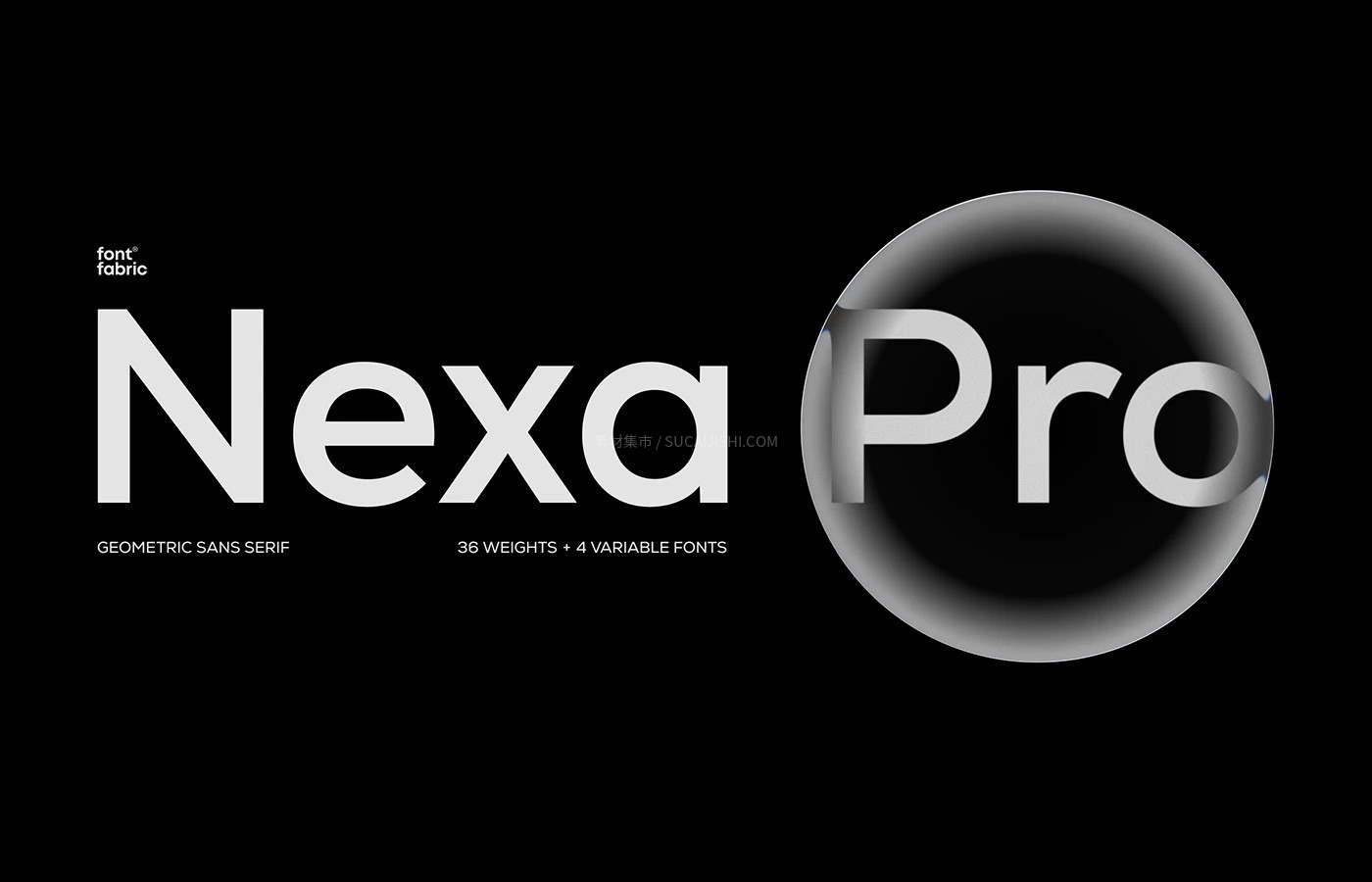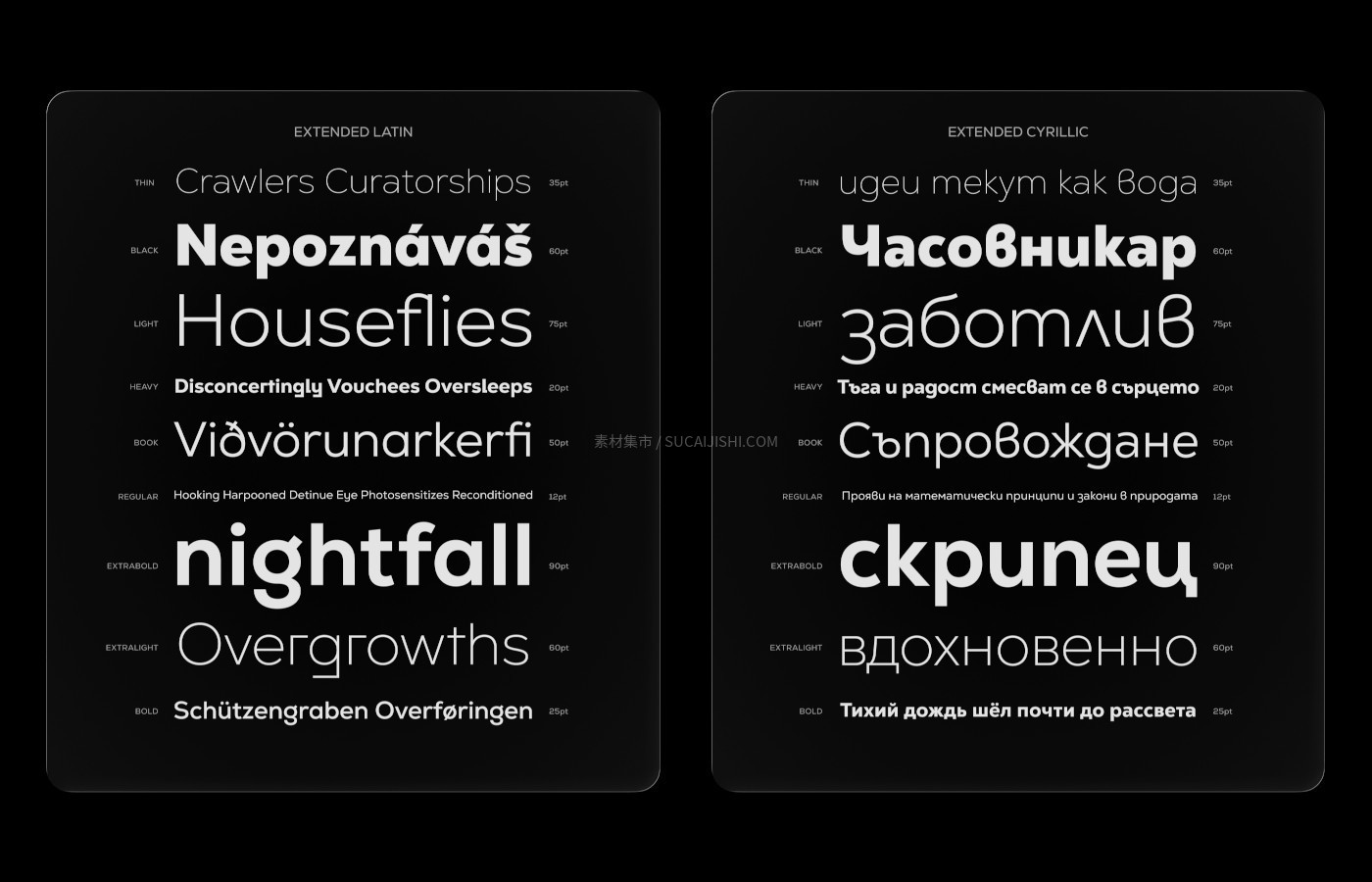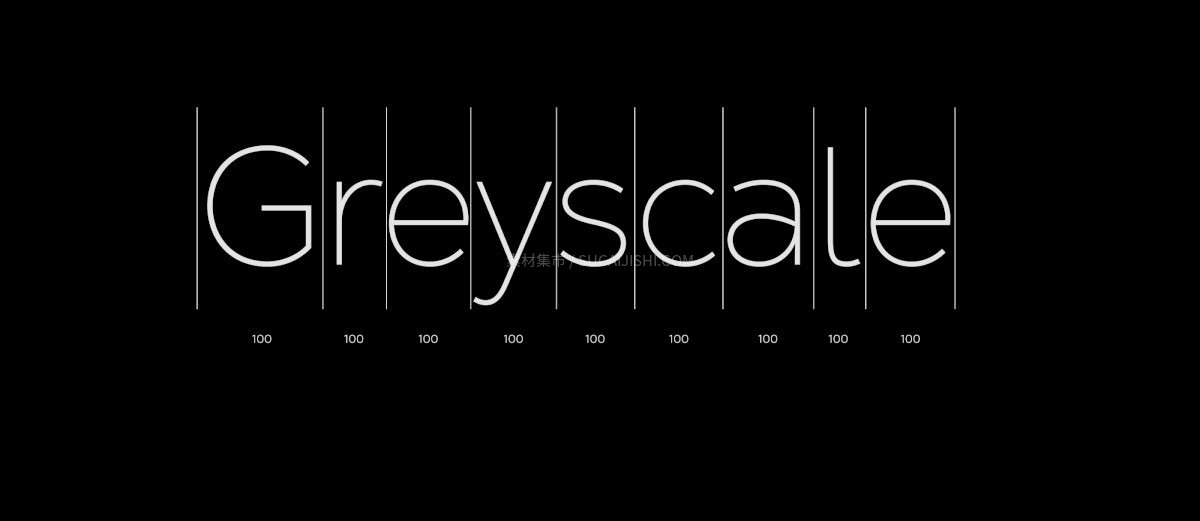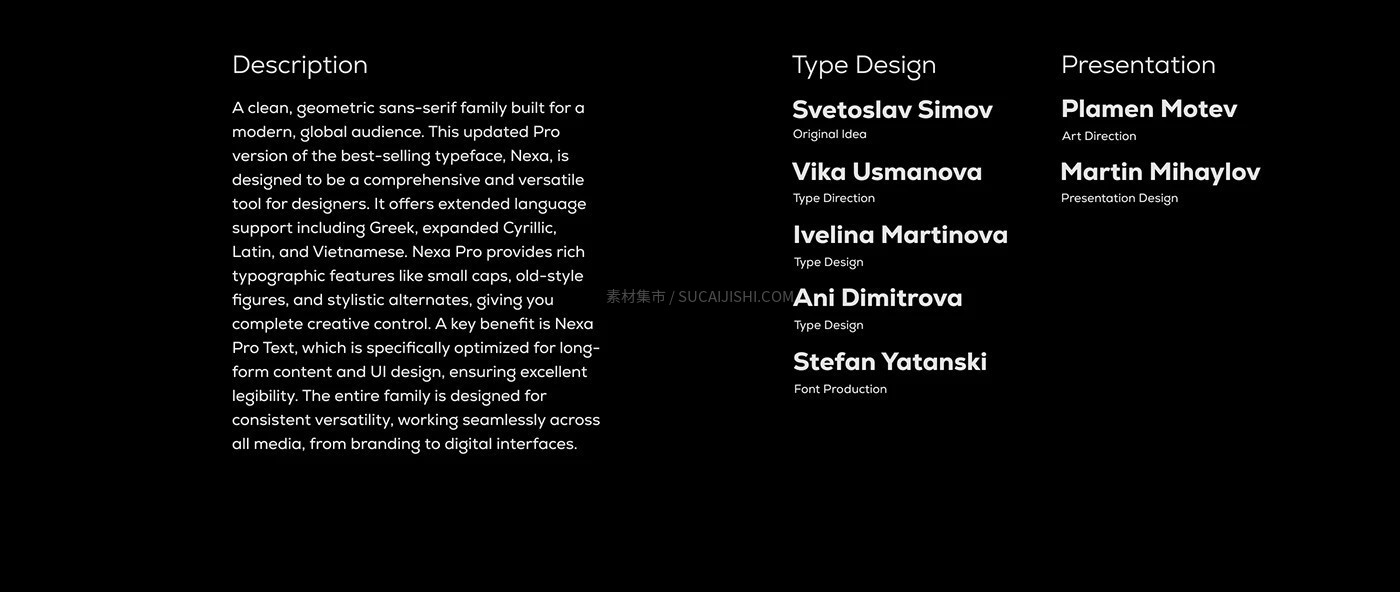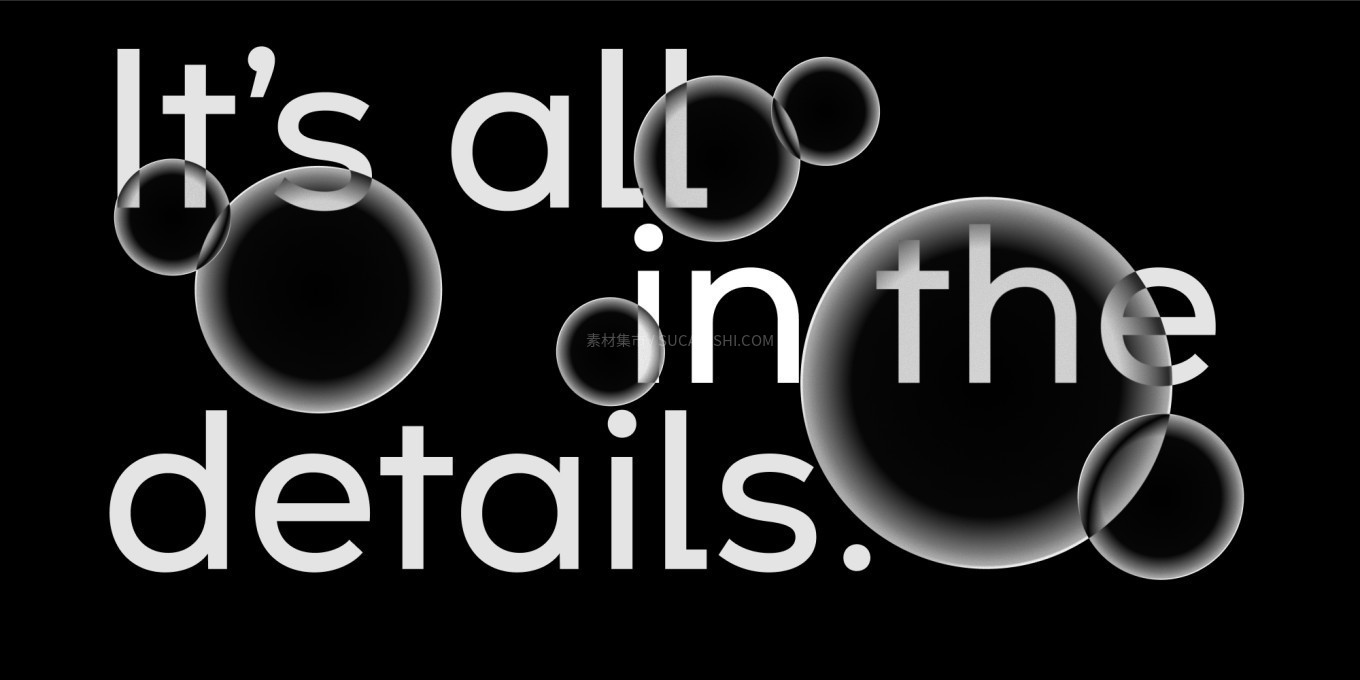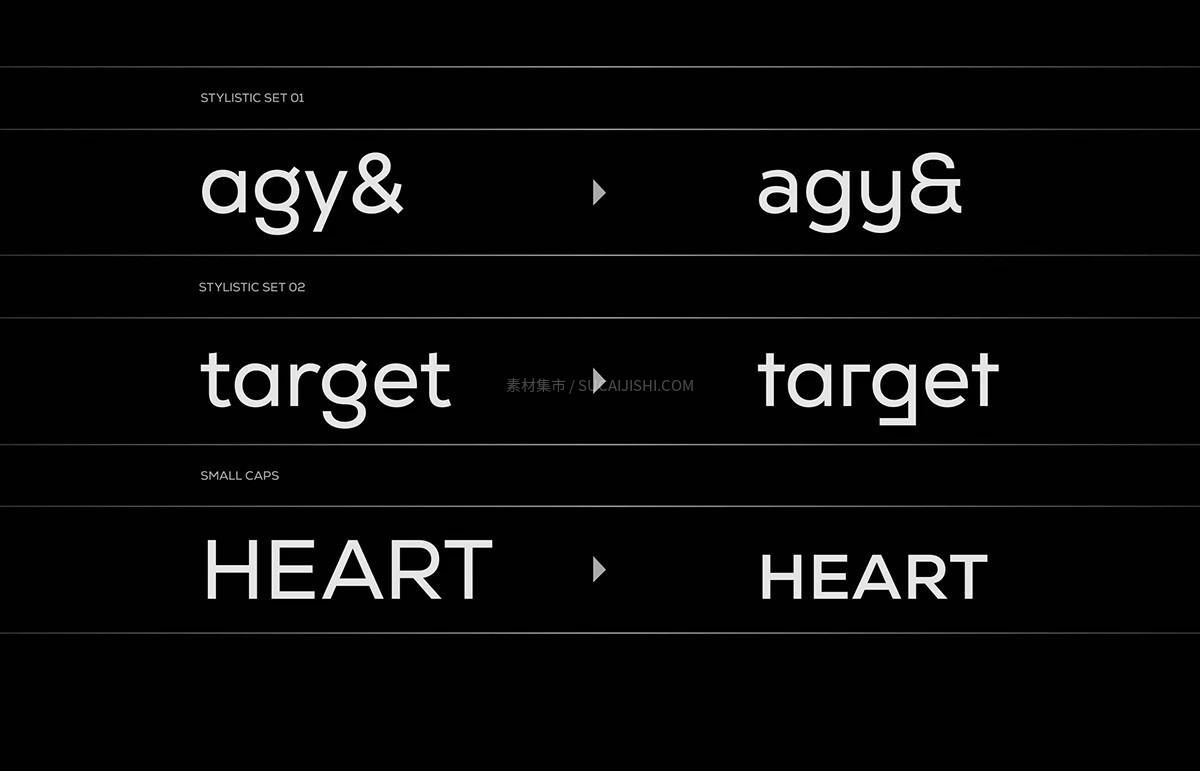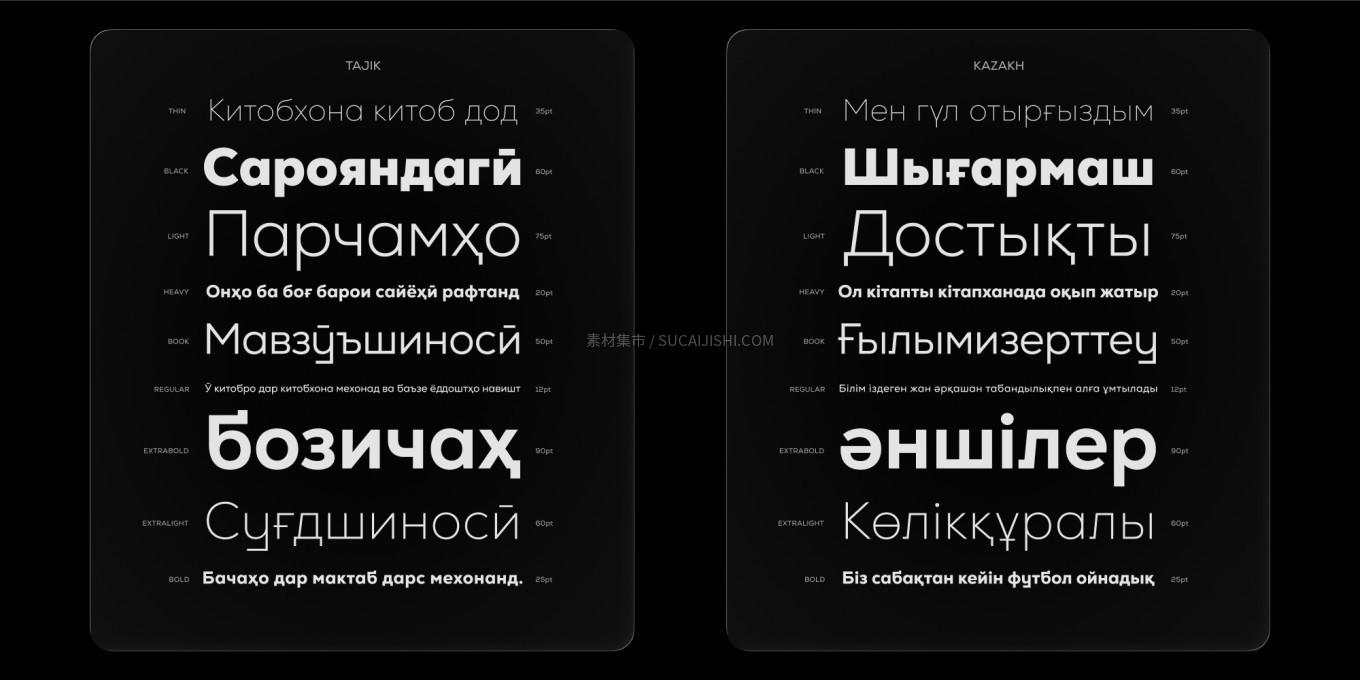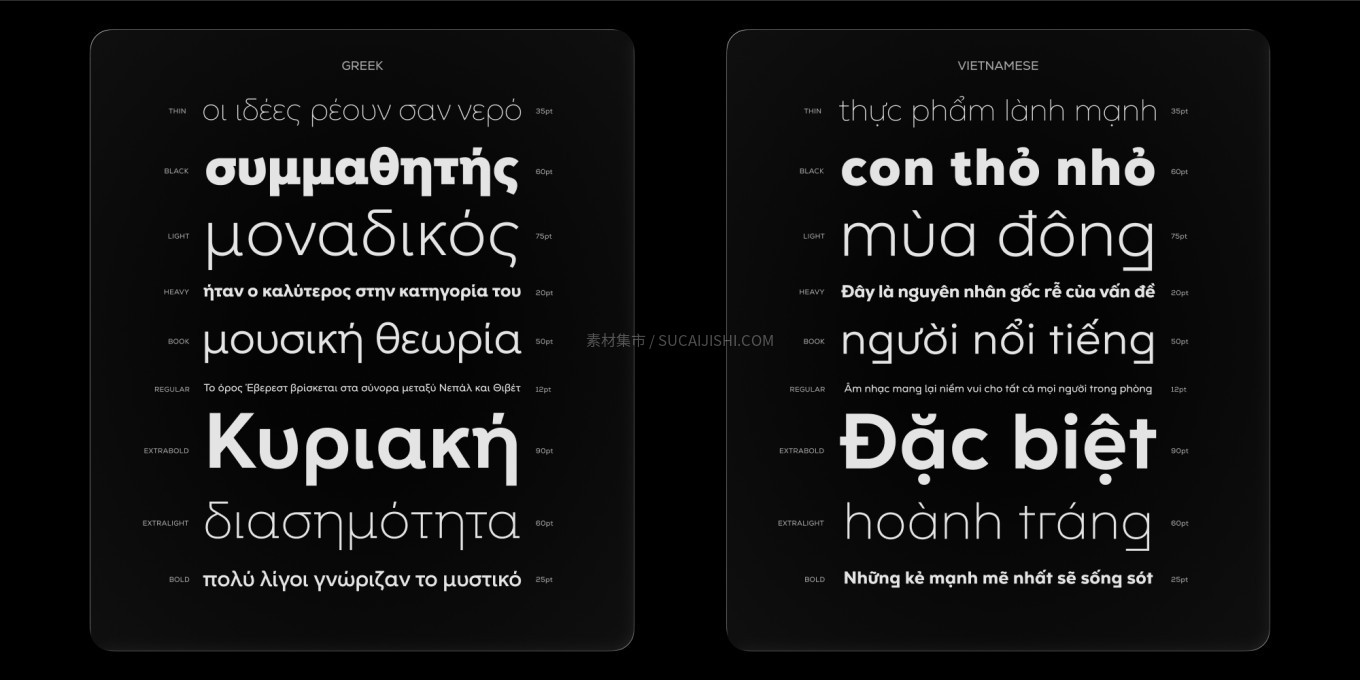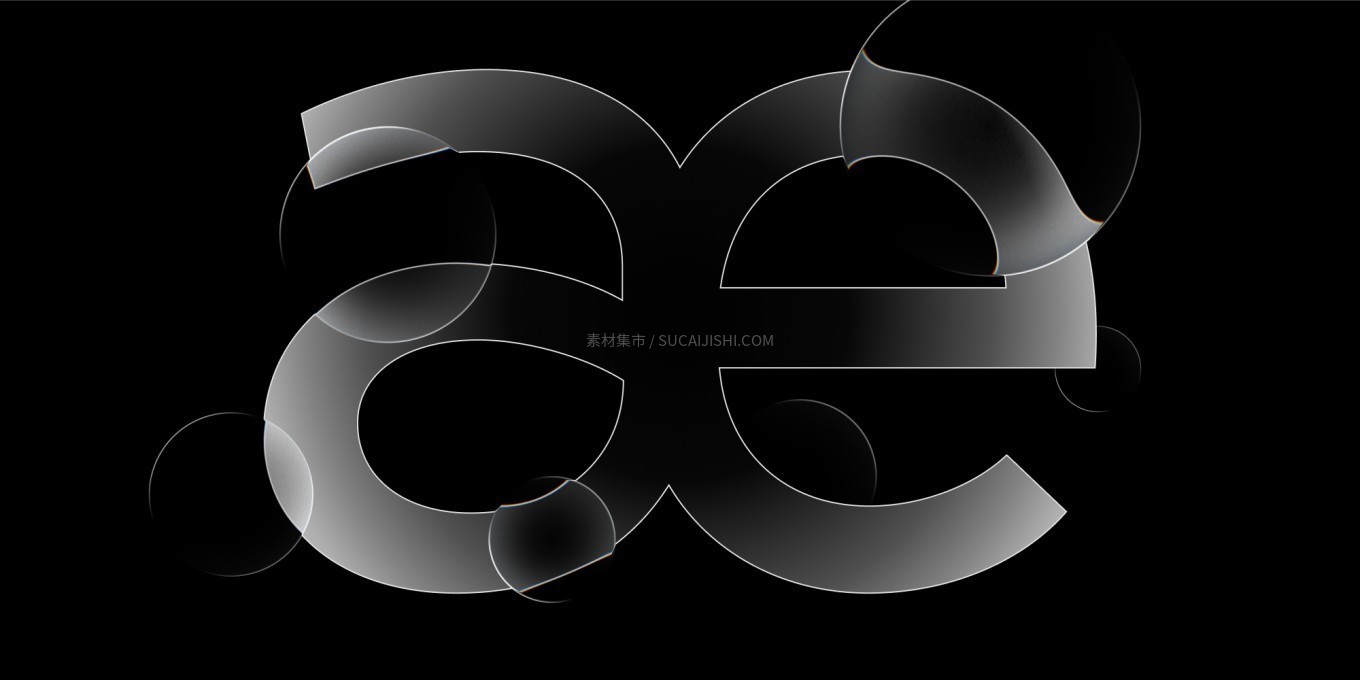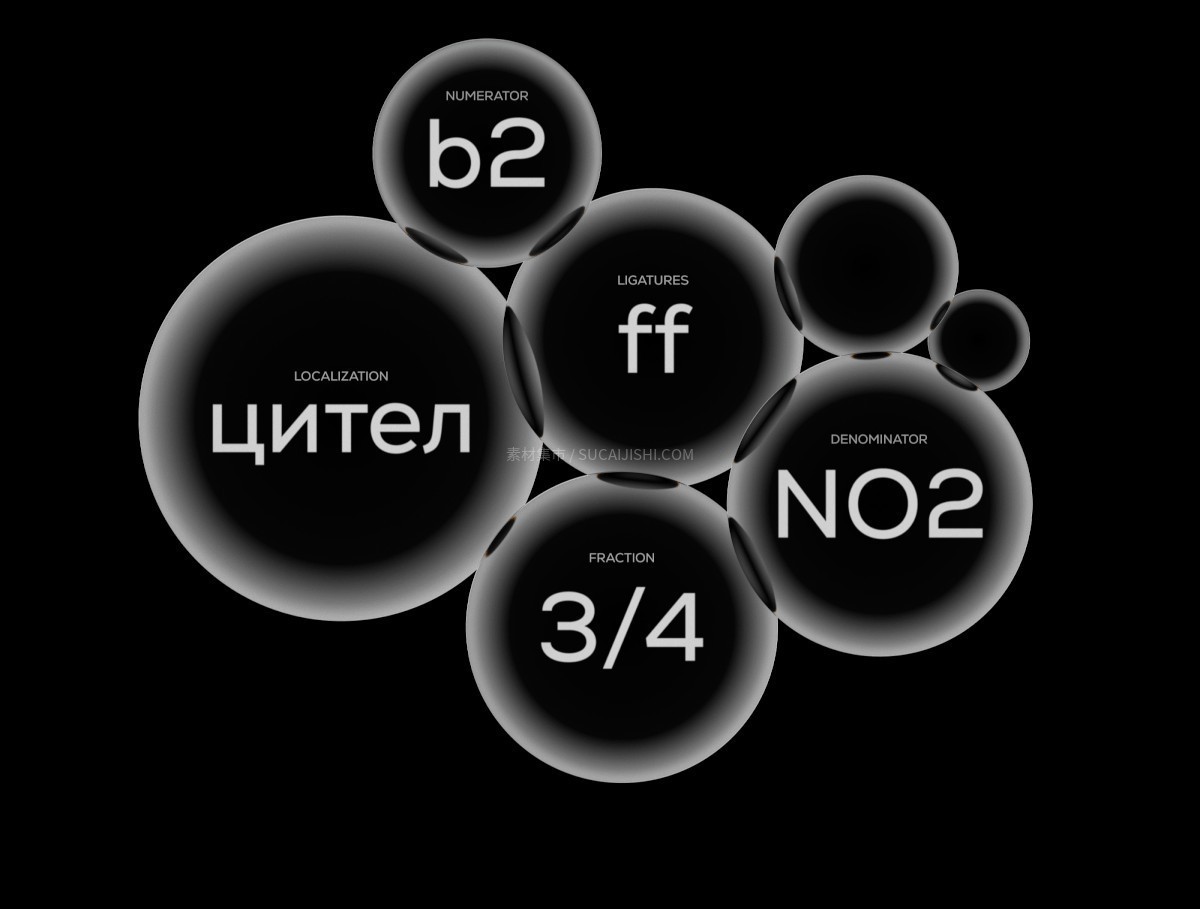
Nexa PRO 几何无衬线可变字体家族
备受赞誉的 Nexa Pro 几何无衬线字体迎来全新升级!包含 36 款静态字重(OTF/Web)与 4 款可变字体(TTF)。它秉承了简洁现代的设计理念,不仅对曲线细节进行了精细化打磨,还新增了小大写字母、旧式/带圈数字、划线零以及更广泛的多语言支持(含扩展西里尔文、越南语、希腊语等)。